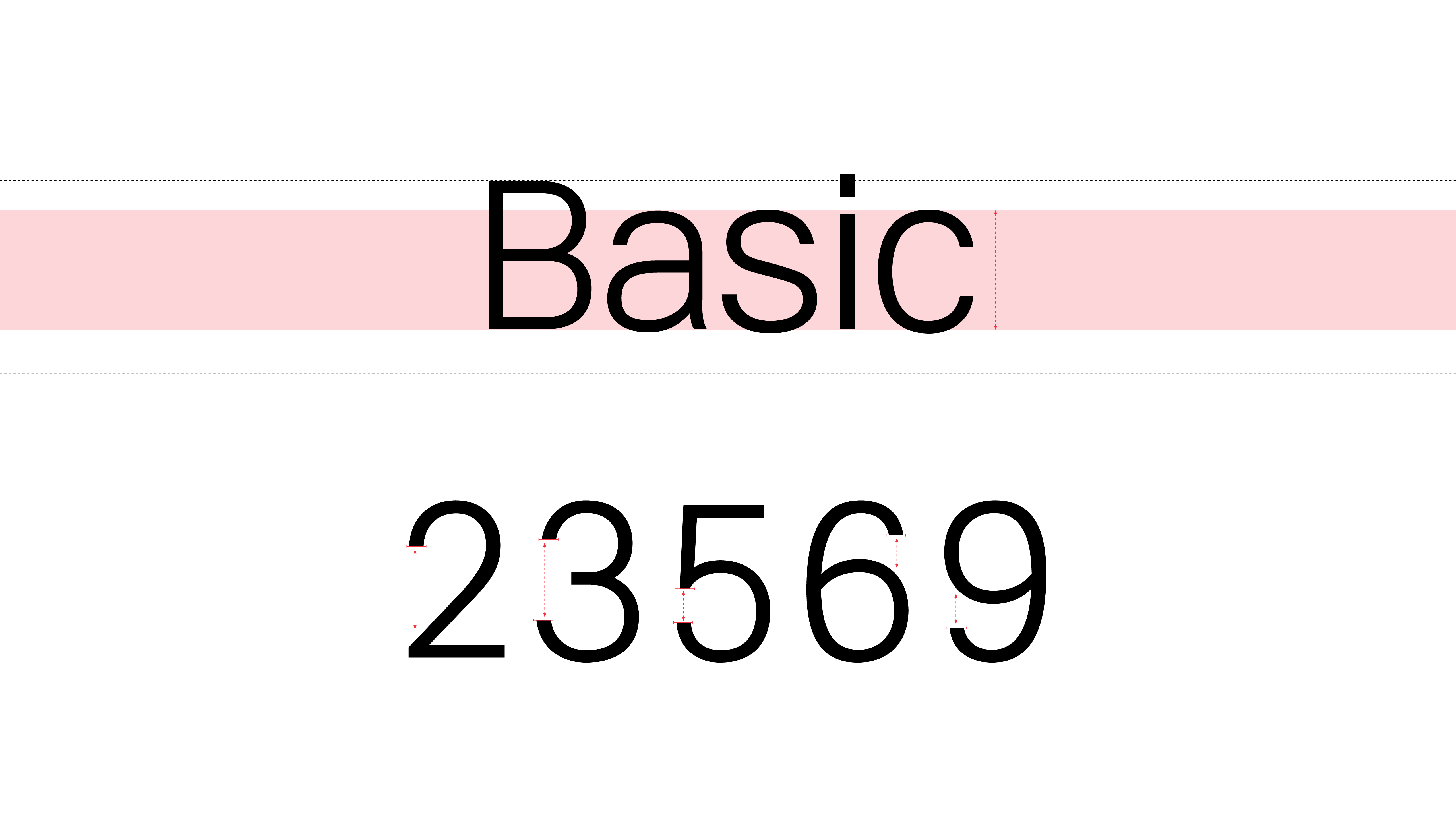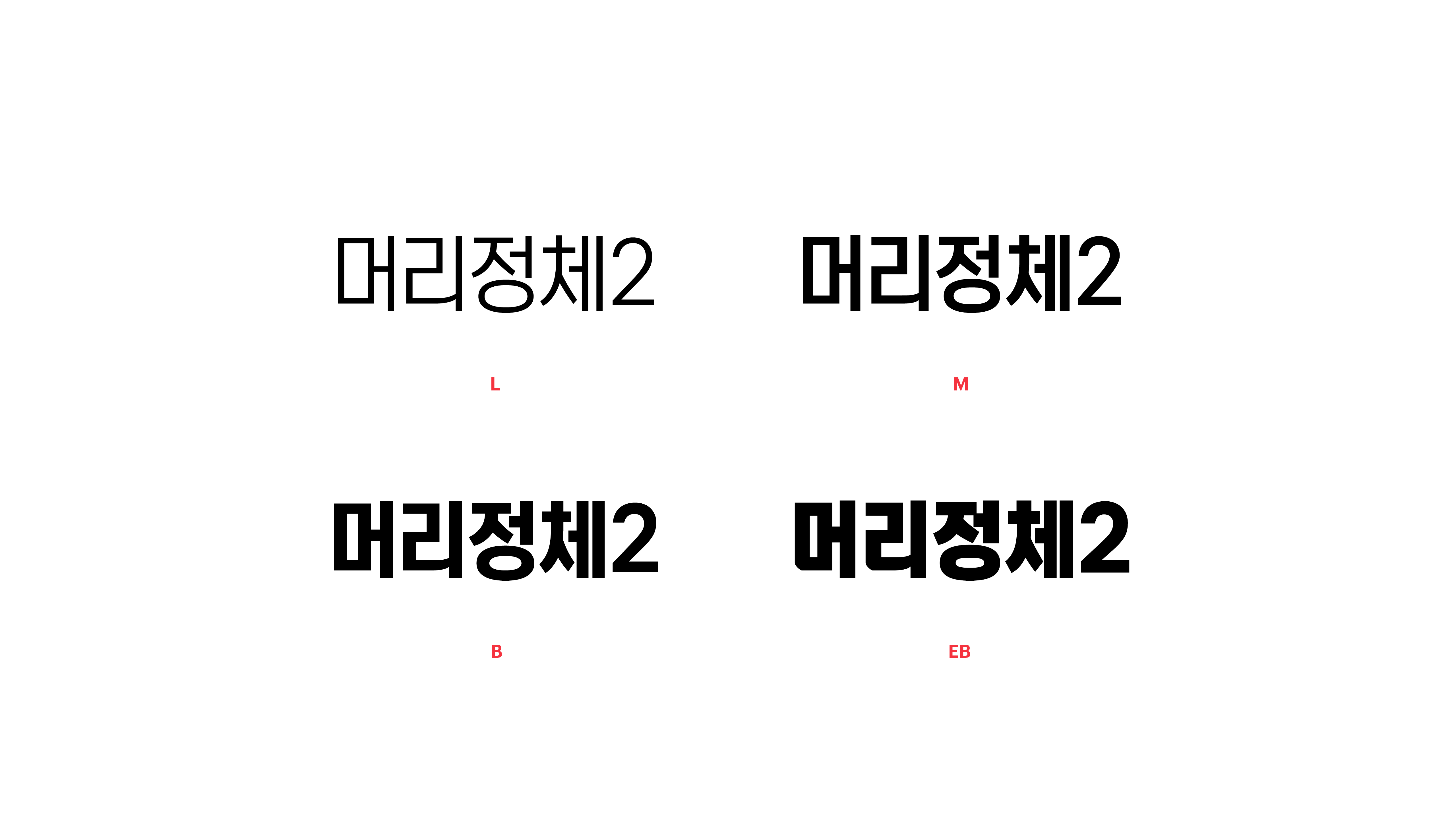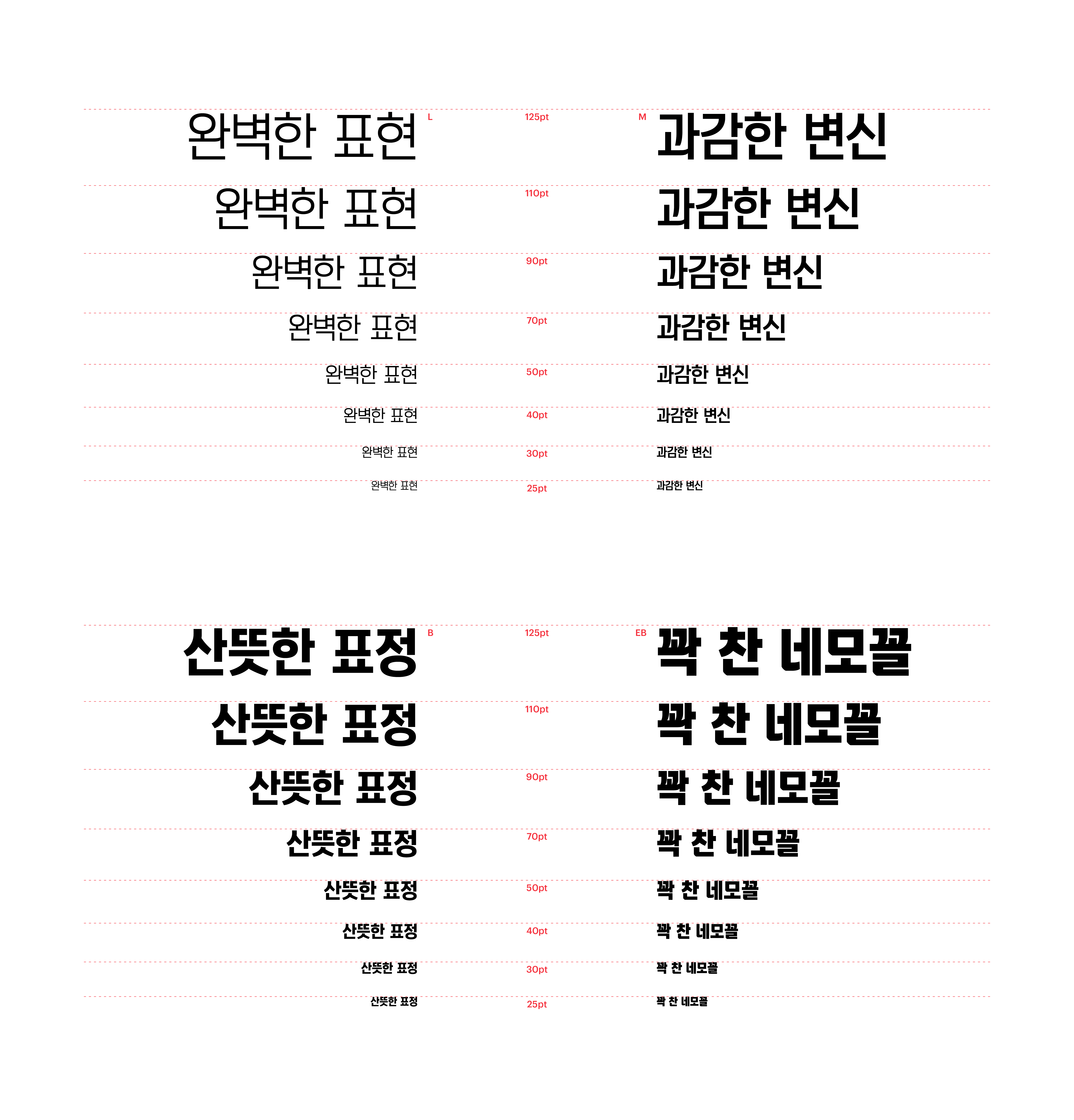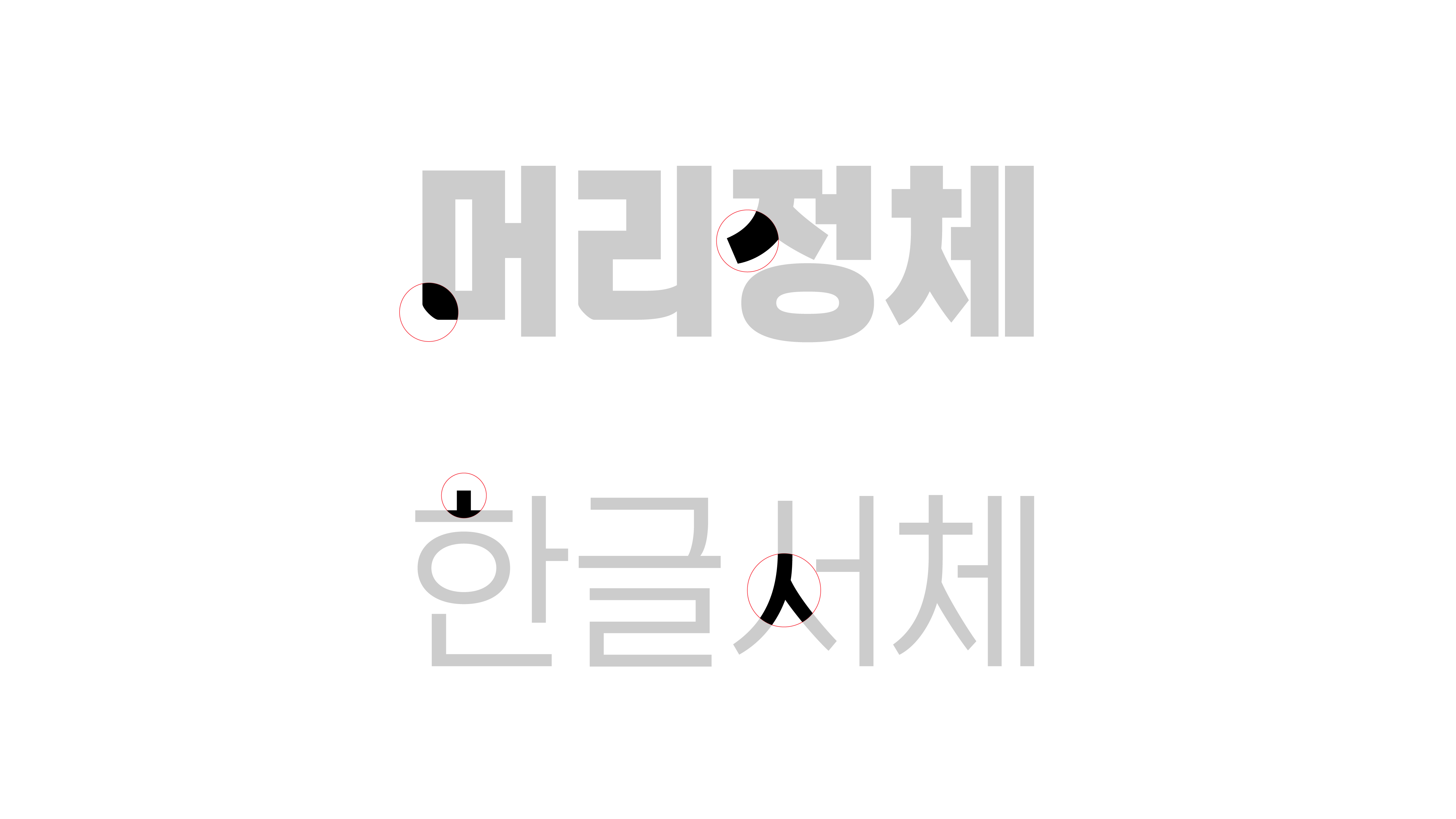
머리정체 2
Yoon 머리정체 2
인쇄물의 헤드라인, 빵빵 터지는 방송 자막, 우리 가게의 산뜻한 표정이 되어줄 간판과 옥외광고 등. 널리 널리 알려야 할 소식들을 위한 폰트가 준비되었습니다. 기존의 머리정체를 보다 꽉 찬 네모꼴로 단단하게 벼려 제목 전용 폰트로 재구성했지요. 제목 표현의 신세계로 떠나는 티켓, 머리정체2에 숨겨져 있답니다.